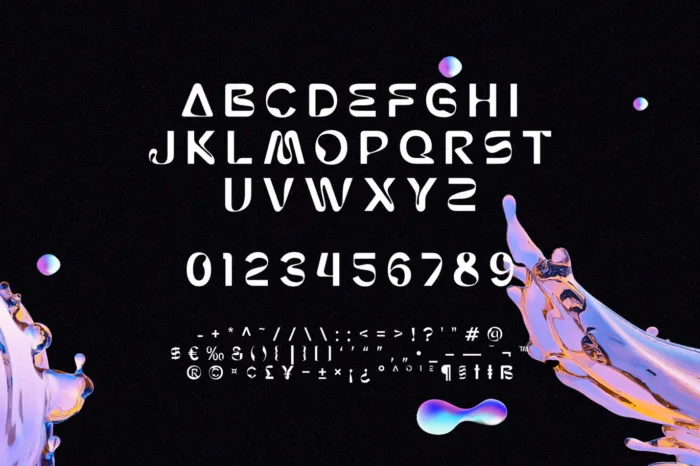
DVN Liquid Việt hóa – Font chữ phong cách chất lỏng
DVN Liquid là một font chữ độc đáo mang phong cách tương lai với những đường nét lỏng chảy đầy sáng tạo. Lấy cảm hứng từ chất lỏng kim loại và hiệu ứng phản chiếu, font chữ này mang đến cảm giác hiện đại, công nghệ và đầy tính nghệ thuật.
Các ký tự được thiết kế với sự biến dạng tinh tế, kết hợp giữa hình khối sắc nét và các đường cong mềm mại, tạo nên hiệu ứng thị giác ấn tượng. DVN Liquid phù hợp cho các dự án thiết kế như poster, tiêu đề, branding, ấn phẩm kỹ thuật số và cả các concept về AI, cyberpunk hay metaverse.
Phiên bản Việt hóa đảm bảo giữ trọn vẹn phong cách nguyên bản, đồng thời hỗ trợ đầy đủ dấu tiếng Việt, giúp bạn thoải mái sáng tạo trong mọi ngữ cảnh. Nếu bạn đang tìm kiếm một font chữ mang lại sự khác biệt và đậm chất nghệ thuật, DVN Liquid chính là lựa chọn lý tưởng!